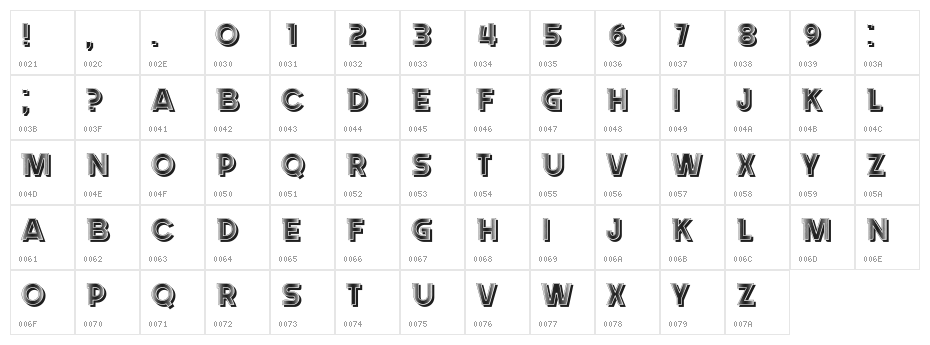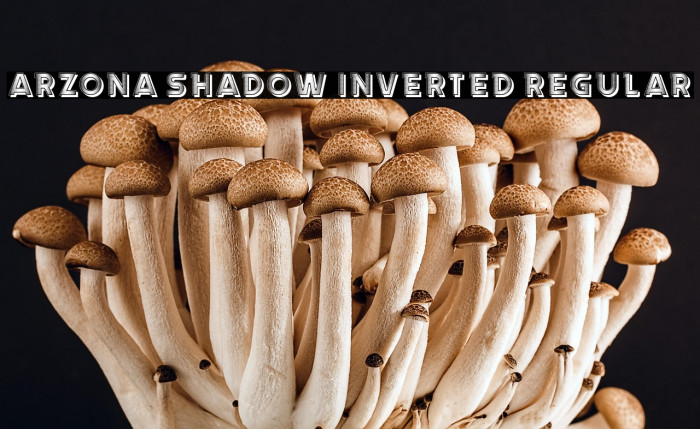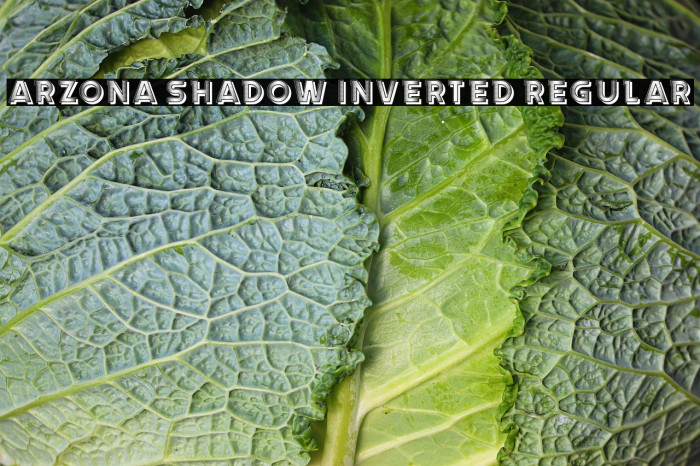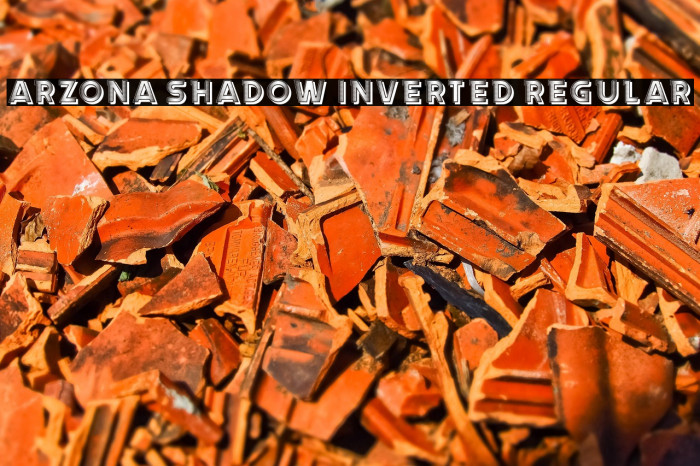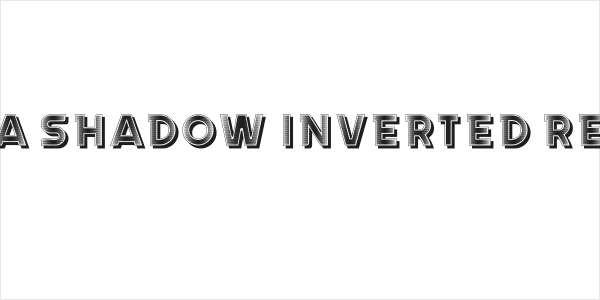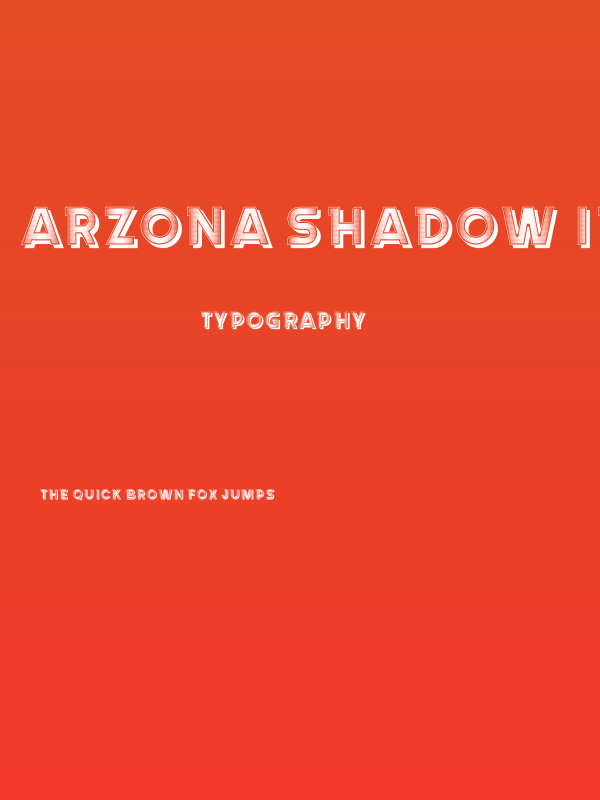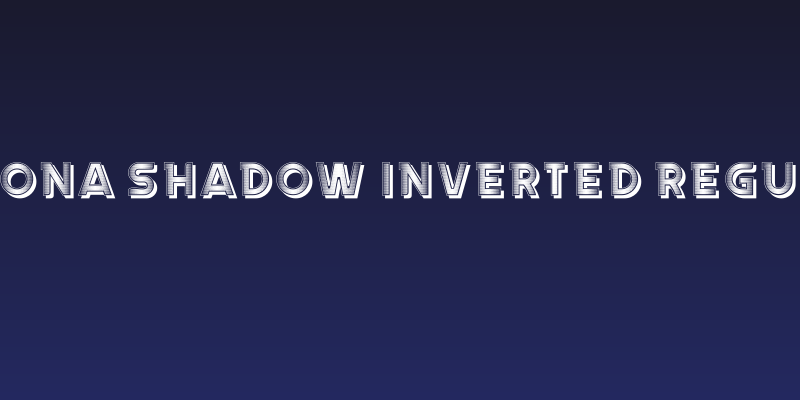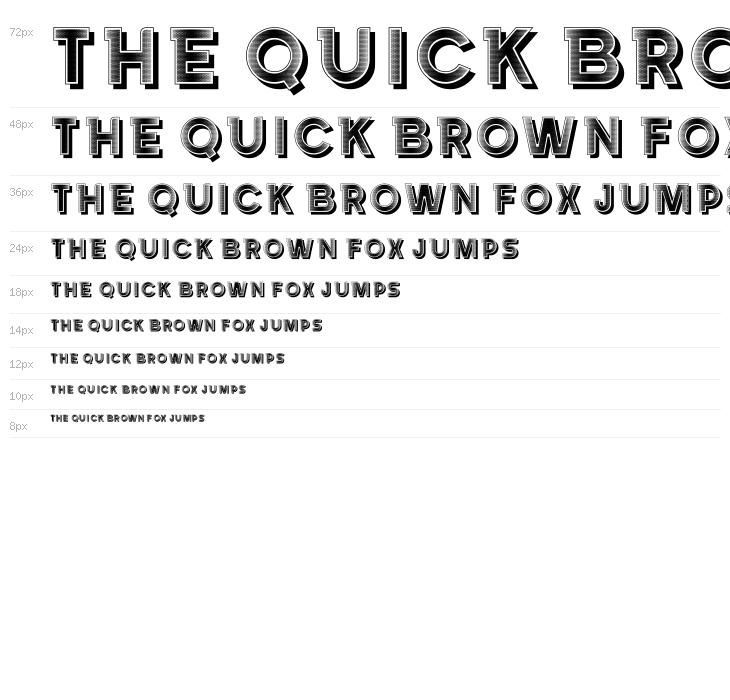
Arzona Shadow Inverted Regular Font
| Progetti proposti | Ideal for posters, logos, and branding materials where a strong visual impact is desired. |